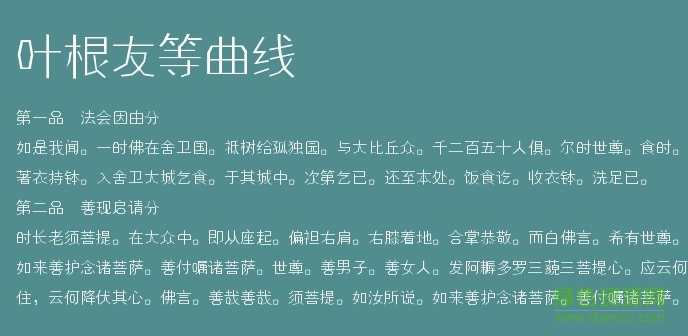
葉根友等曲線字體是一款古典線條風格字體軟件,等曲線體筆畫非常細膩整潔,整體效果比較清新耐看,實用于正規(guī)文章書寫,深受廣大書法家喜愛,還有更多好看字體歡迎來綠色資源網(wǎng)下載體驗!
葉根友等曲線字體是一款個性特征明顯的字體,采用筆畫線條多段直線彎曲的創(chuàng)意進行設計,是標題用字以及其他個性海報用字不錯的選擇。該字體會不定期更新,歡迎關注。